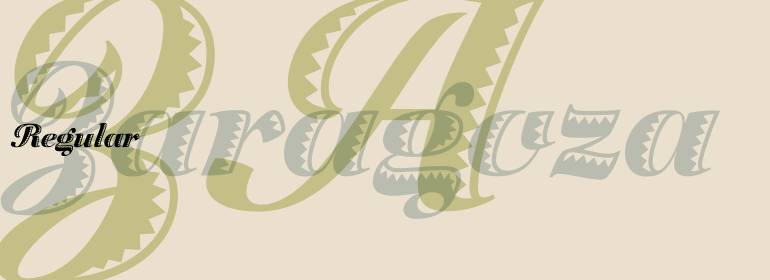
Zaragoza™
Zaragoza是英国设计师Phill Grimshaw的作品,这是一款大胆而精美的手写体,字符内有锯齿形装饰。大写字母与小写字母的风格协调一致。
Zaragoza is the work of British designer Phill Grimshaw, a bold and beautifully rendered script which incorporated an internal zigzag decoration. Generous capitals harmonize with a lowercase that should be set close to reproduce the look of true handwriting.